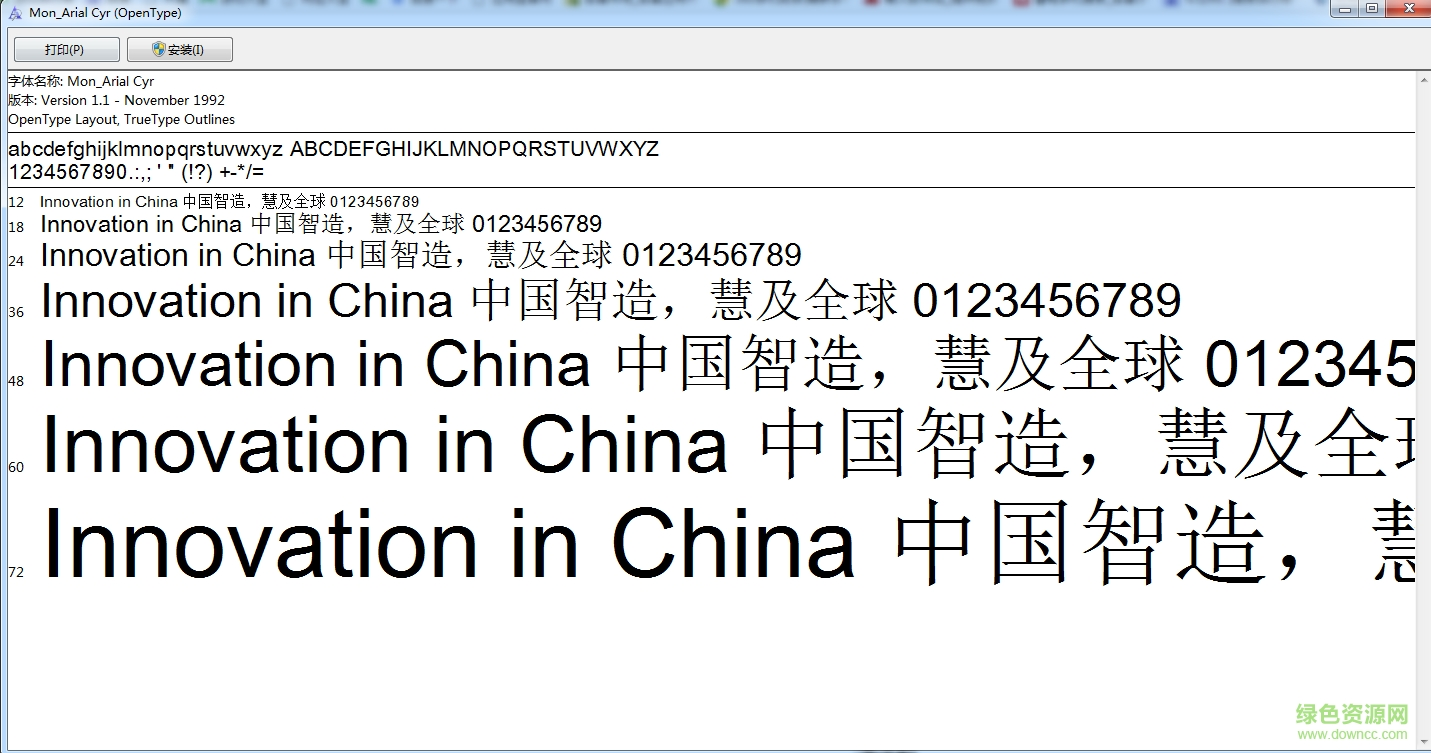
arial cyr 普通字體是一款美觀的英文無襯線字體,字形優(yōu)雅好看,線條勾勒清晰,轉(zhuǎn)角柔和構(gòu)思精美,常常用于排版設(shè)計(jì)中,歡迎大家在綠色資源網(wǎng)下載!
【Arial Rounded】:包含Arial Rounded Bold(粗體),此字體可在微軟韓文字體Gulim找到
【Arial Black】:此字體的特色在于其筆畫相當(dāng)?shù)拇?,包含Arial Black、Arial Black Italic(斜體)
【Arial】:有時(shí)稱為Arial Regular以便與Arial Narrow區(qū)別,其包括Arial、Arial Italic(斜體)、Arial Bold(粗體)、Arial Bold Italic(粗斜體)和Arial Unicode MS
【Arial Narrow】:為Arial的細(xì)瘦版本,包含Arial Narrow Regular、Arial Narrow Bold(粗體)、Arial Narrow Italic(斜體)和Arial Narrow Bold Italic(粗斜體)